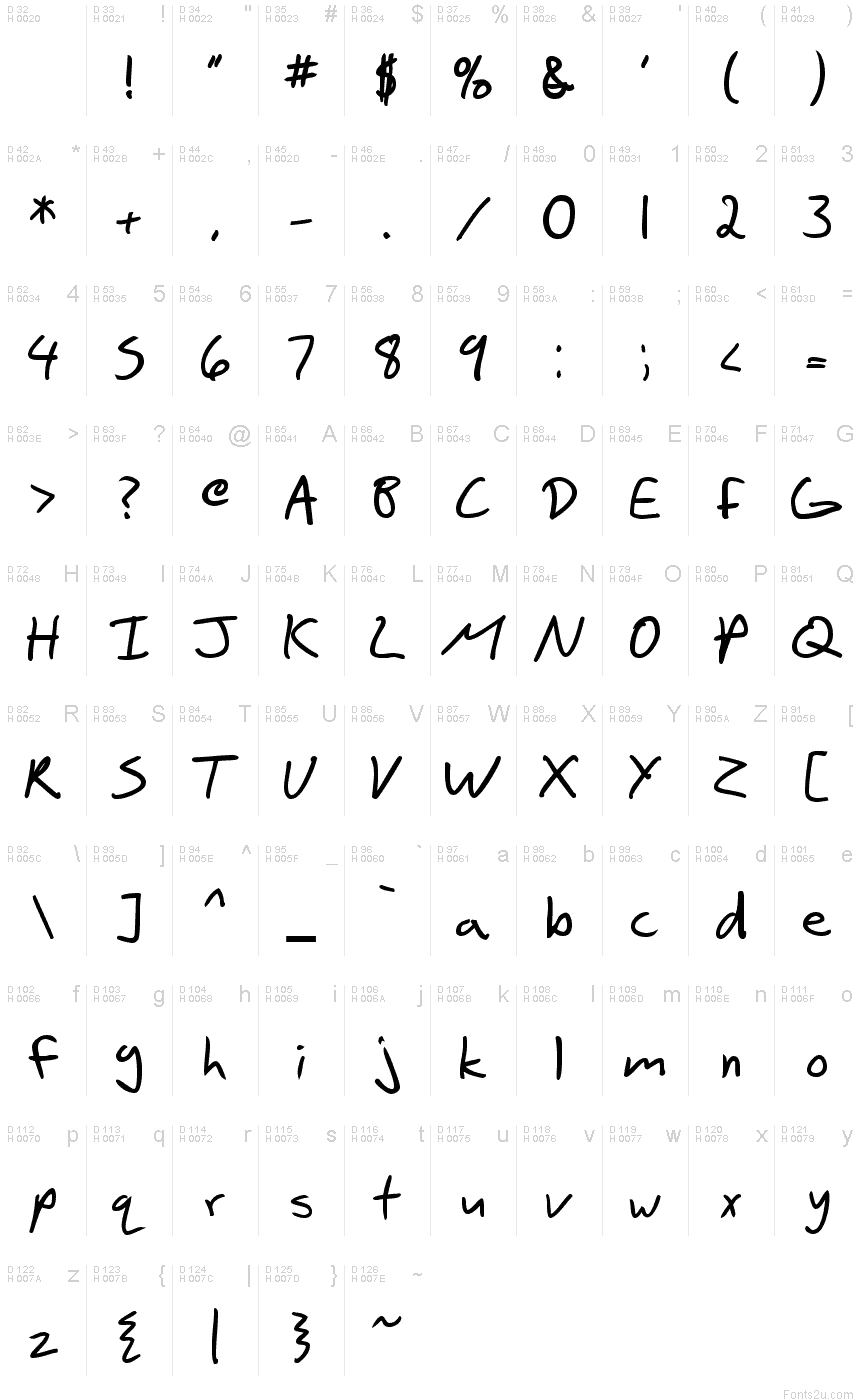
SF Scribbled Sans Bold od ShyFoundry to darmowy, odręczny krój bezszeryfowy, który oddaje szybki, nieregularny charakter notatek robionych markerem, kreślonych jednym pociągnięciem. Litery są szerokie i luźne, z zaokrąglonymi łukami, tępymi łączeniami i lekko skaczącym rytmem, co nadaje całości swobodny, a nie wygładzony wyraz.
Świetnie pasuje do zinów, plakatów, okładek albumów, opakowań i młodzieżowego brandingu, gdzie darmowy font powinien być nieformalny i ludzki, a nie idealnie poukładany. Wykorzystaj go w krótkich nagłówkach, tekstach na okładkach, tytułach czy wyróżnionych cytatach, zwłaszcza jeśli szukasz grubych, odręcznych kształtów, które wyglądają na spontaniczne, ale nie przypominają brush scriptu.
SF Scribbled Sans
SF Scribbled Sans Bold